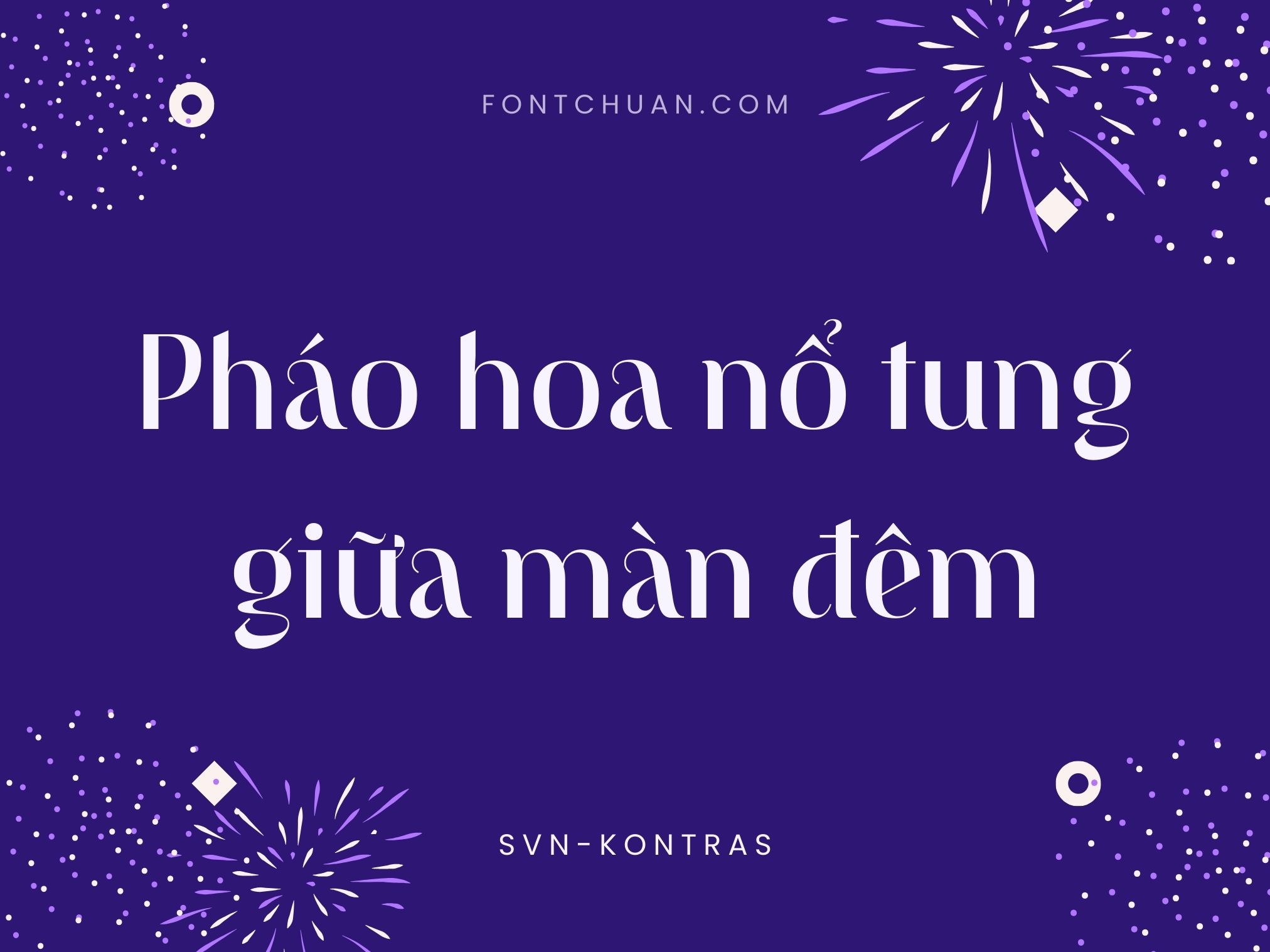
Font SVN Kontras Việt Hóa
Tác giả Font: Kontras
Font SVN Kontras là phiên bản Việt hóa của kiểu chữ Kontras, được thực hiện bởi STYLEno.1 Fonts. Kontras là một kiểu chữ hiển thị với độ tương phản cao giữa các nét dọc và ngang, tạo nên sự độc đáo và thu hút trong thiết kế. Font này bao gồm các ký tự chữ hoa, chữ số và dấu câu, hỗ trợ đa ngôn ngữ. Với thiết kế đặc trưng, Kontras phù hợp cho nhiều mục đích sử dụng như thiết kế tiêu đề, logo, bao bì sản phẩm và các ấn phẩm truyền thông. Đặc biệt, khi kết hợp cùng Font chữ viết tay, Kontras mang đến sự cân bằng giữa nét cá tính mạnh mẽ và cảm xúc mềm mại. Trong khi đó, việc ứng dụng Font SVN Kontras làm Font chữ công nghệ lại giúp thiết kế của bạn phát huy tối đa sự hiện đại và chuyên nghiệp trong các dự án sáng tạo.
SVN Kontras lý tưởng cho các dự án thiết kế yêu cầu sự nổi bật và hiện đại, như thiết kế tiêu đề, logo thương hiệu và các ấn phẩm truyền thông. Các ngành nghề như quảng cáo, giáo dục và công nghệ có thể tận dụng font này để tạo điểm nhấn trong thiết kế. Ngoài ra, font cũng thích hợp cho các sự kiện như Tết, Giáng sinh, Halloween và các lễ hội khác.